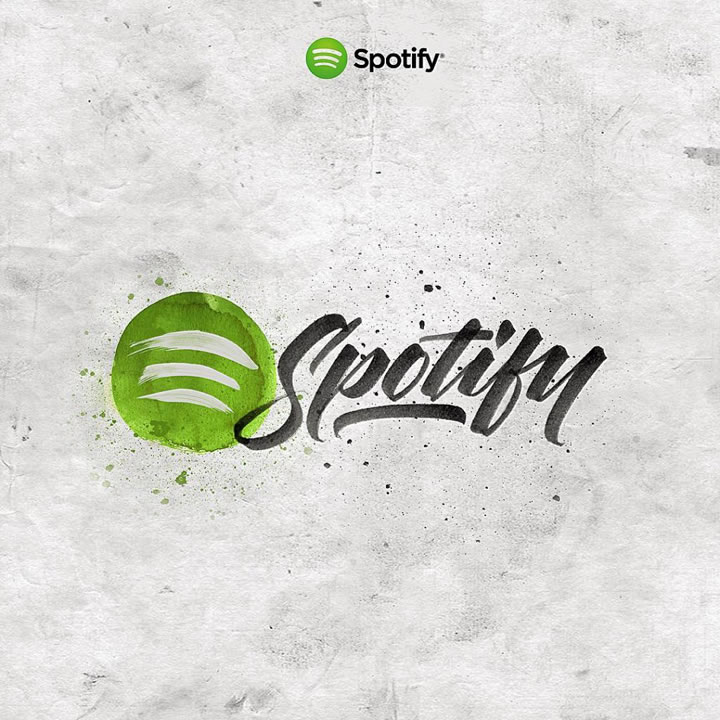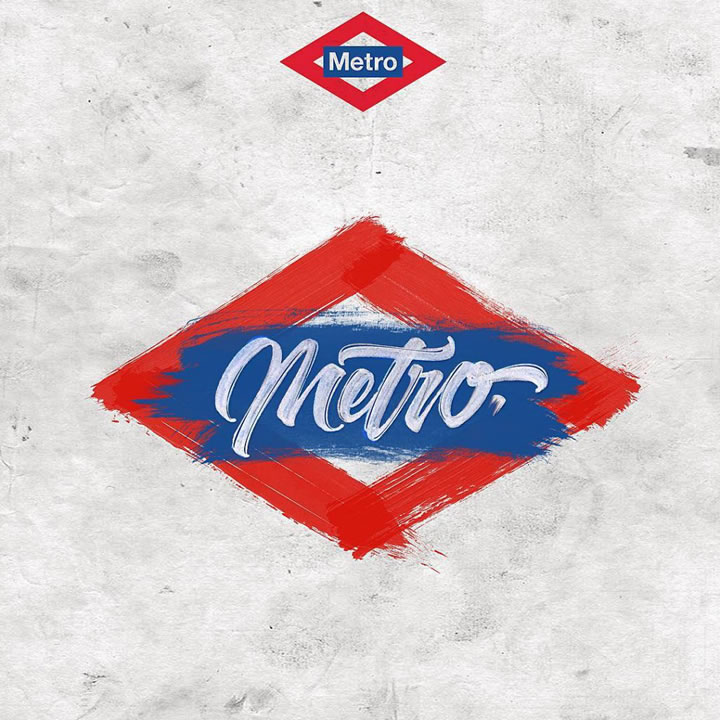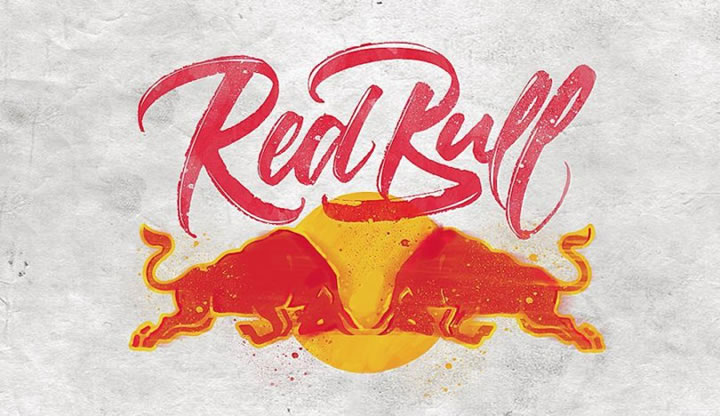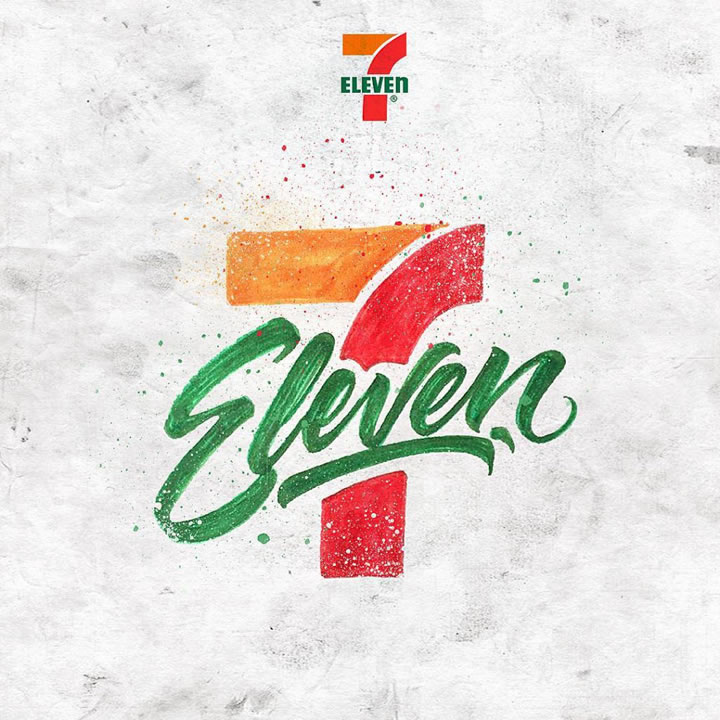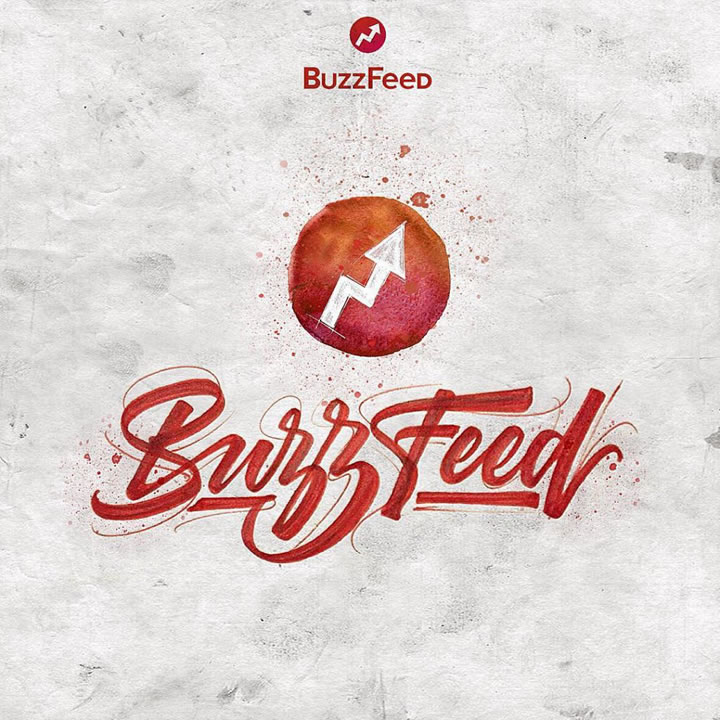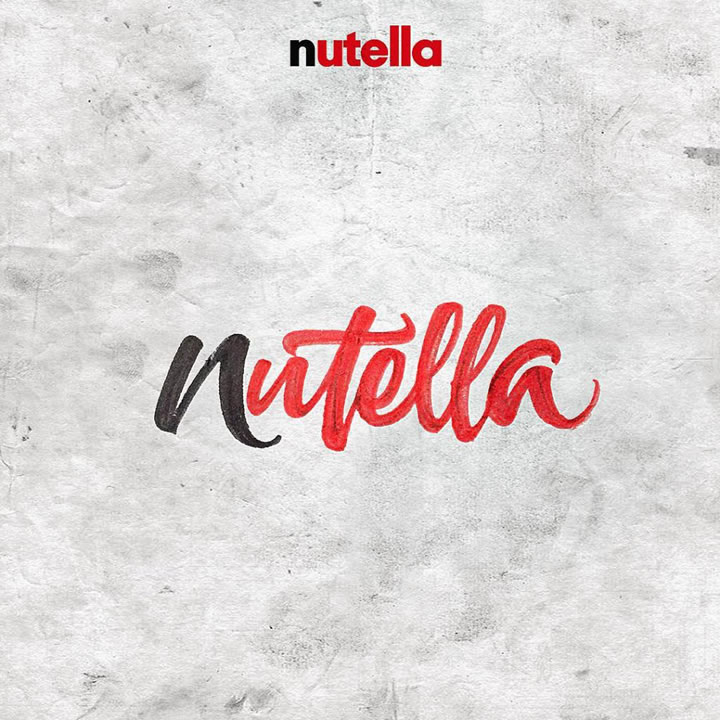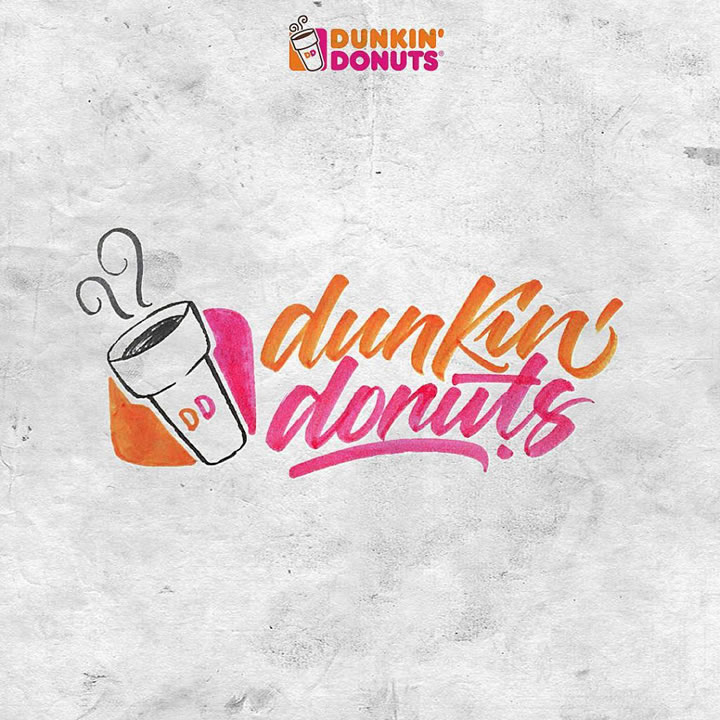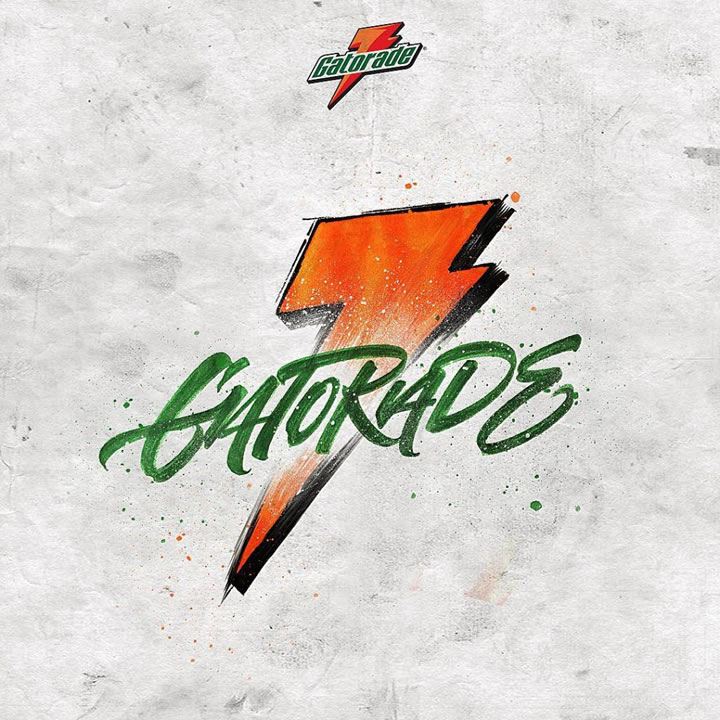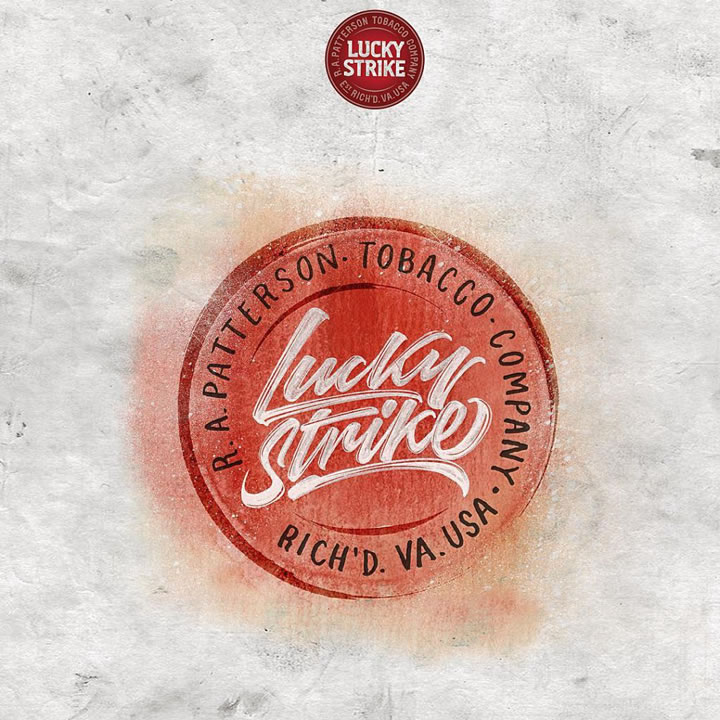
Chouette travail du l’artiste David Milan qui a reprit et retravailler les logos célèbres comme spotify, redbull et bien d’autres dans un style lettering. Un très beau travail à découvrir dans la suite.